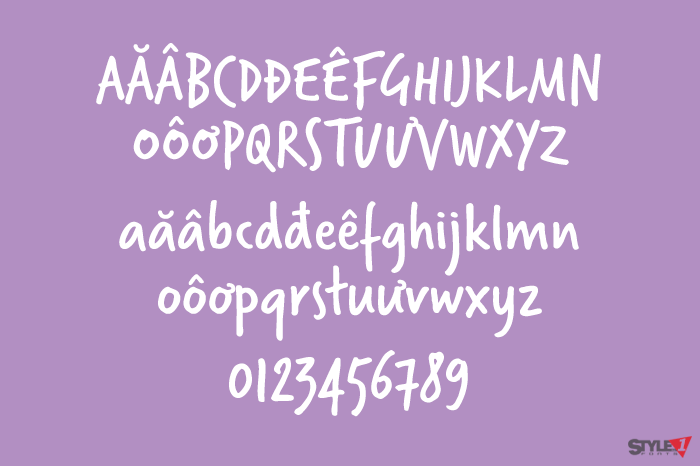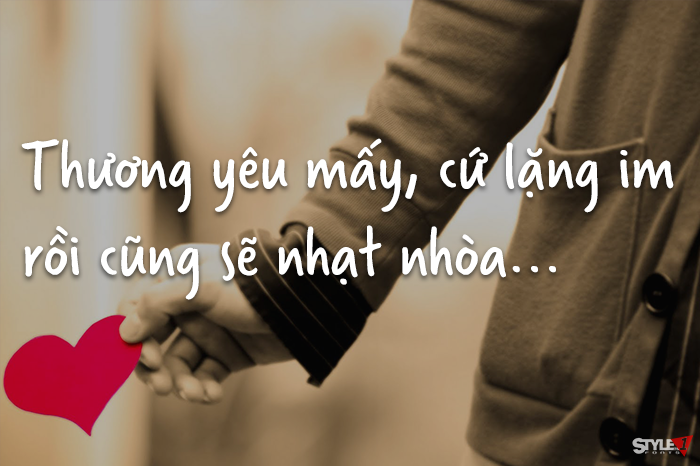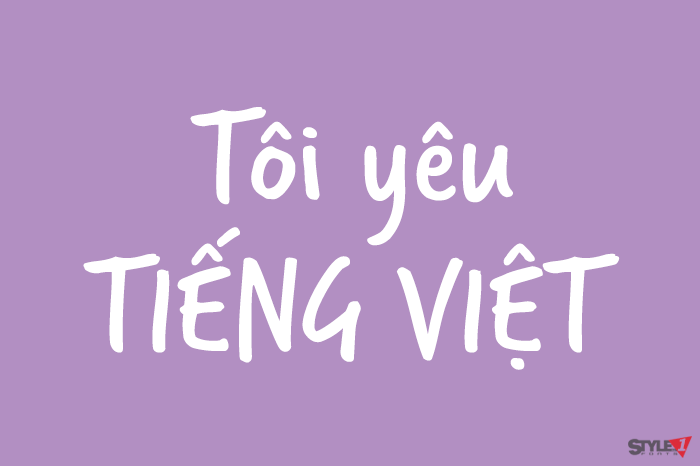
Verveine mang lại cảm giác tươi tắn, nhanh nhẹn với nguồn năng lượng quen thuộc, nhưng dù đầy sức sống, thiết kế của font vẫn được cân nhắc cẩn thận và chặt chẽ. Font phát huy hiệu quả nhất khi dùng cho một vài từ ngắn hoặc một câu tagline.
Nhà thiết kế: Luce Averous
Nhà phát hành: Dalton Maag Ltd.